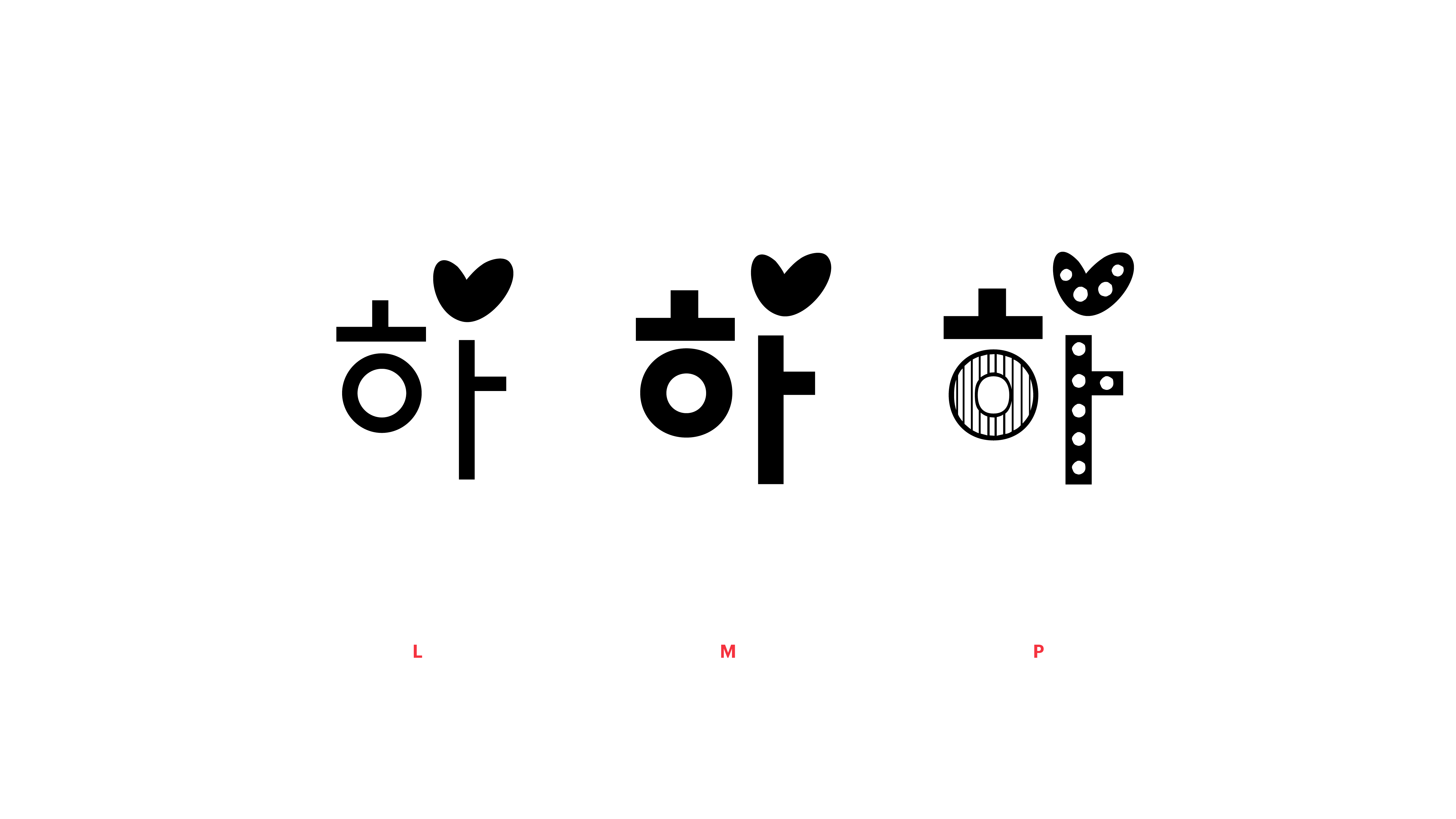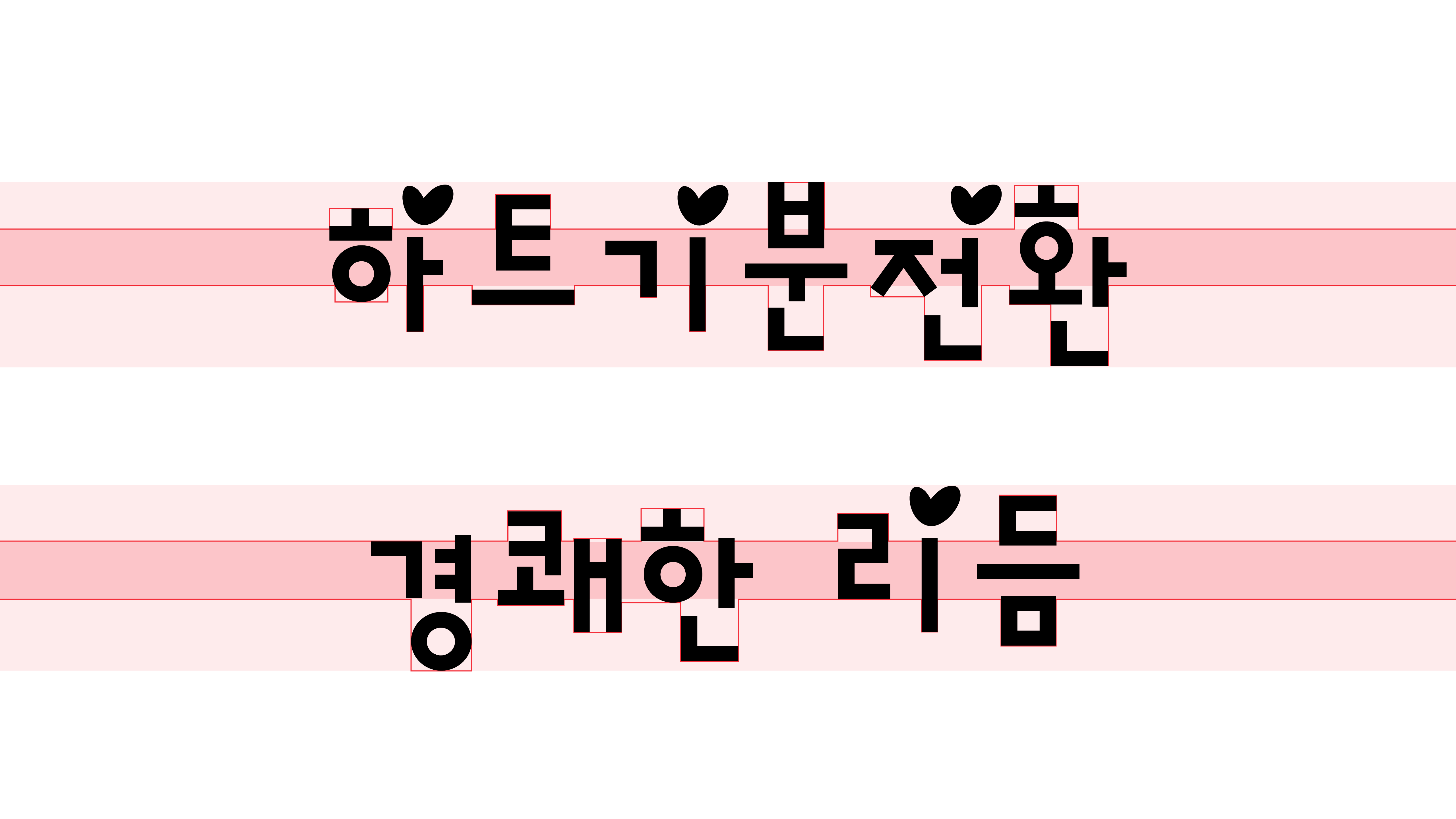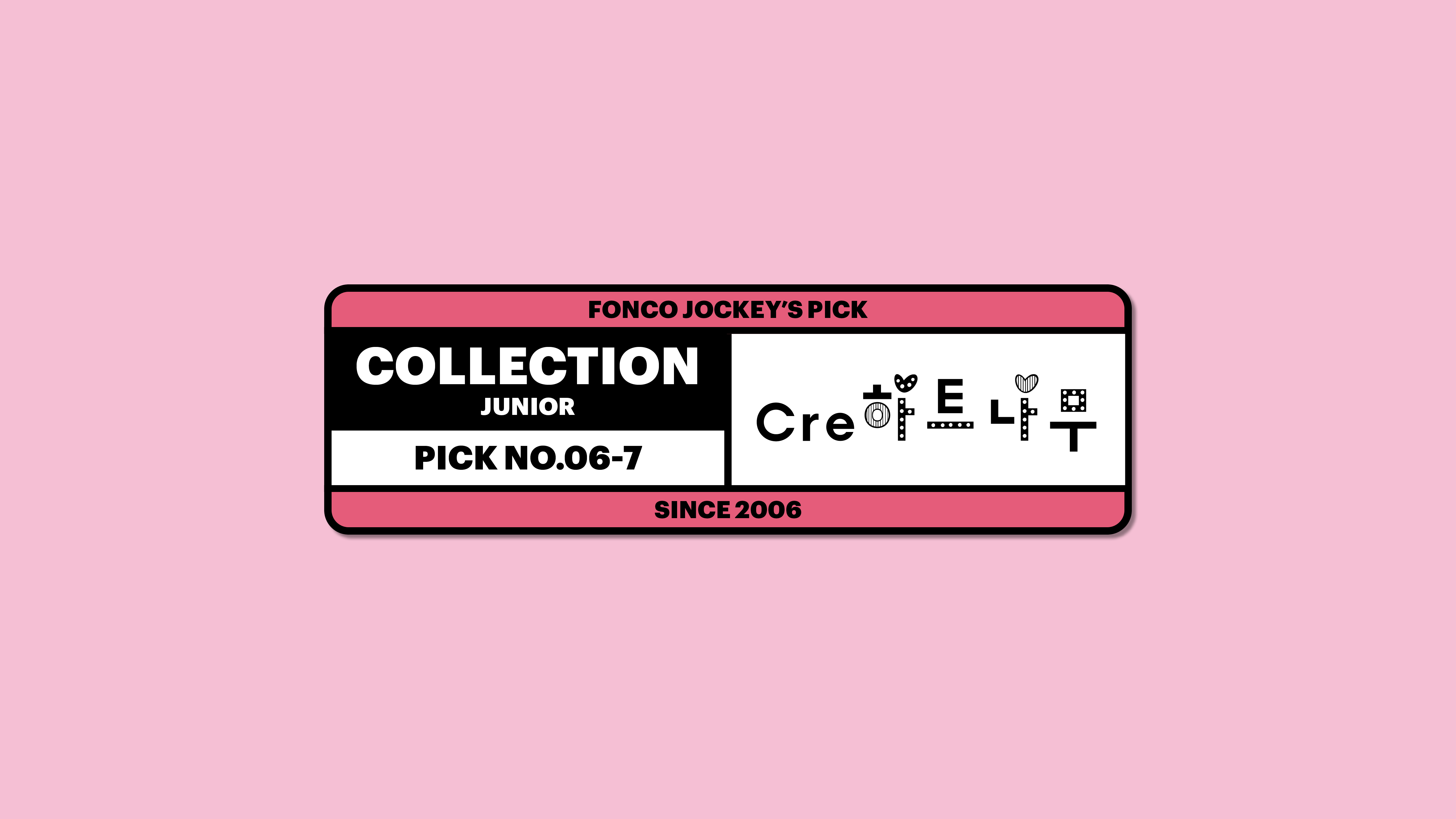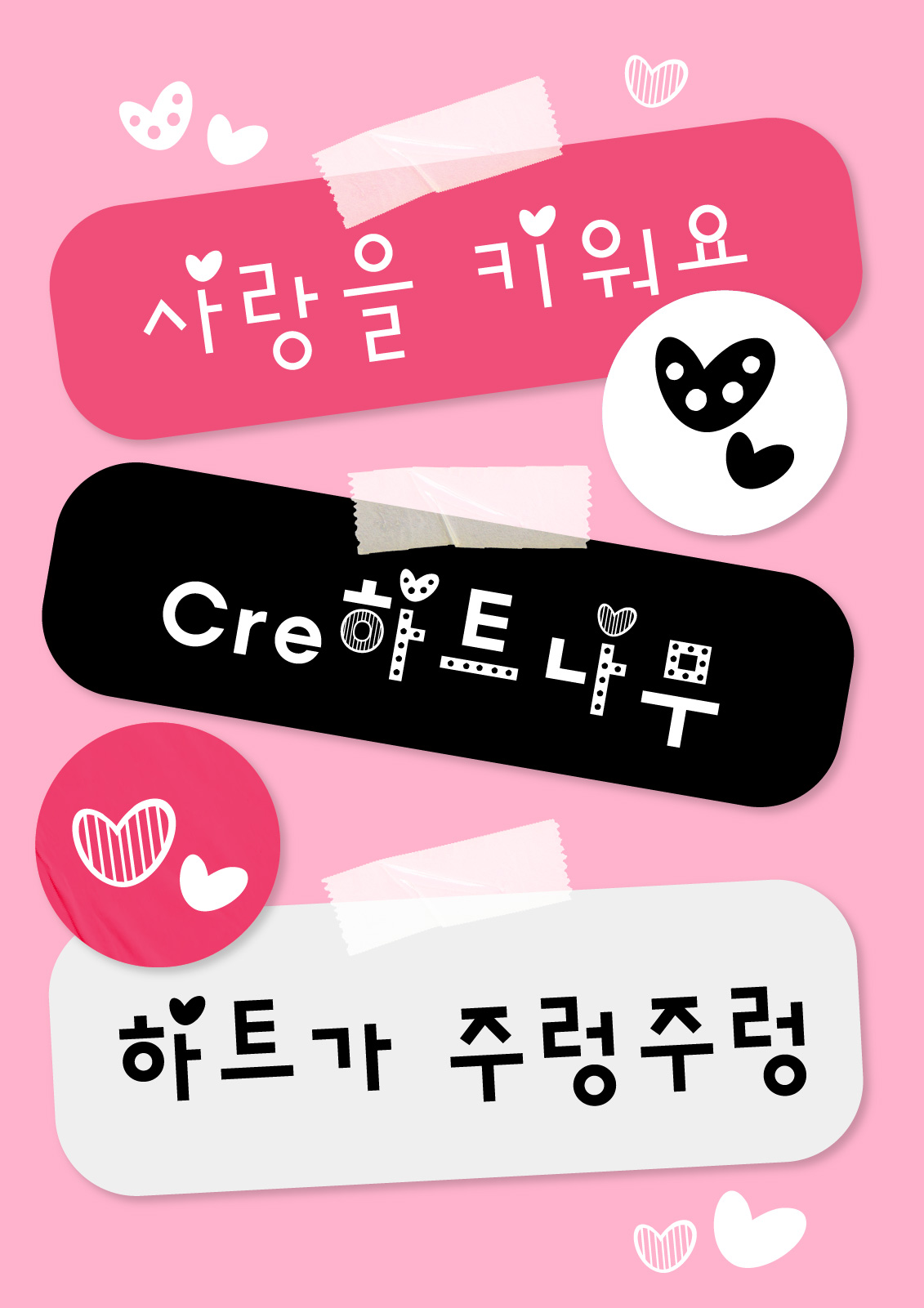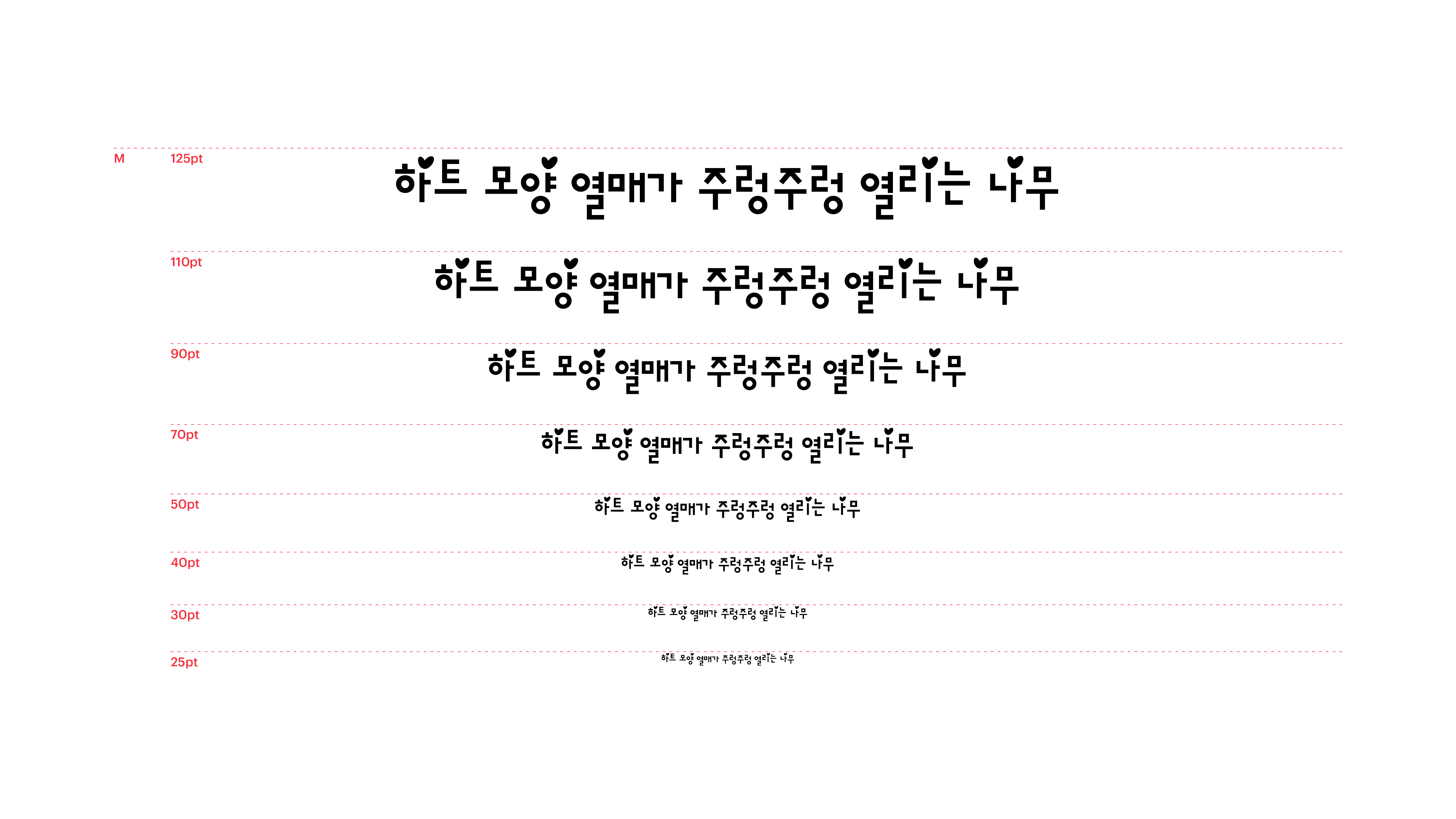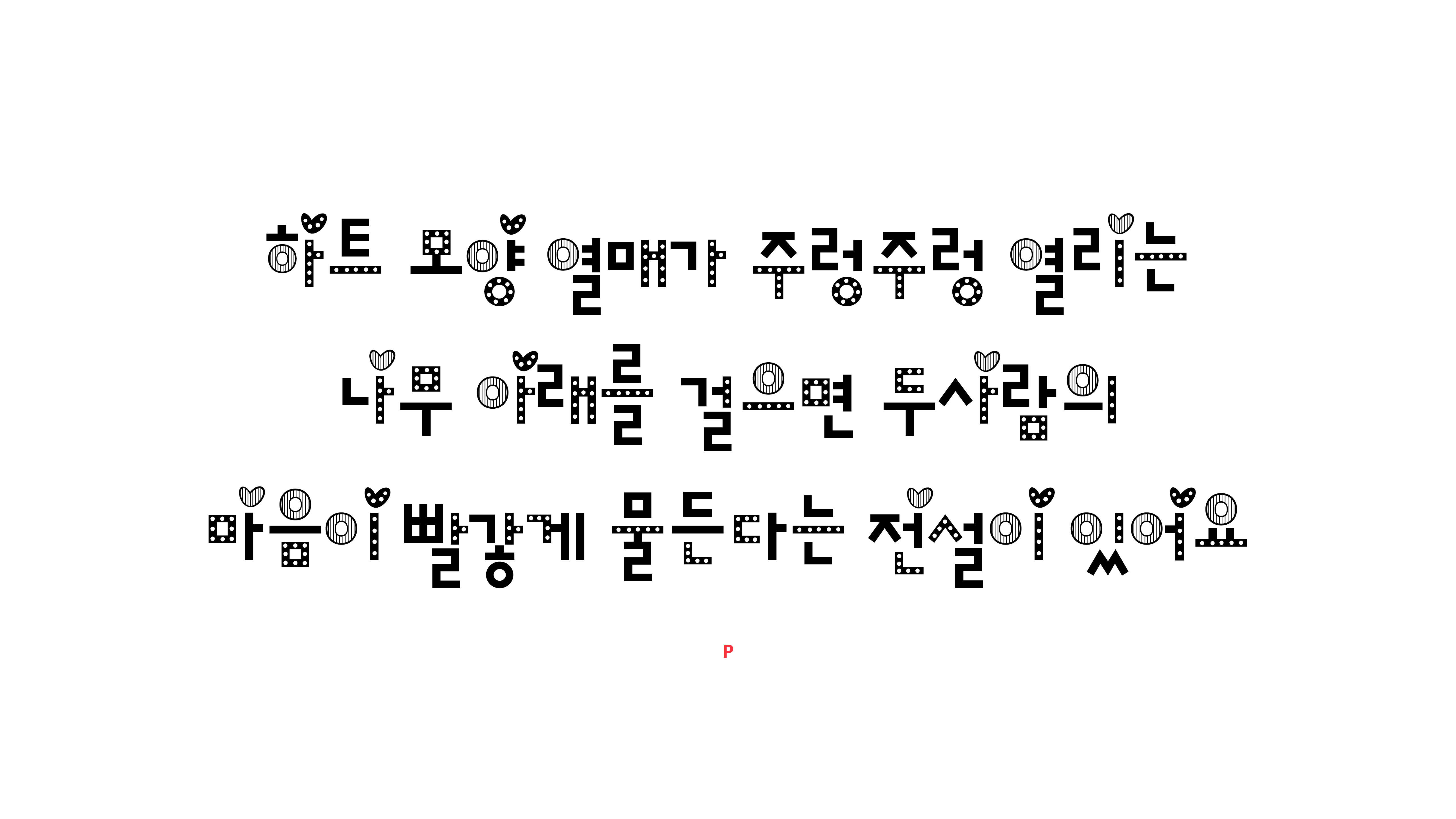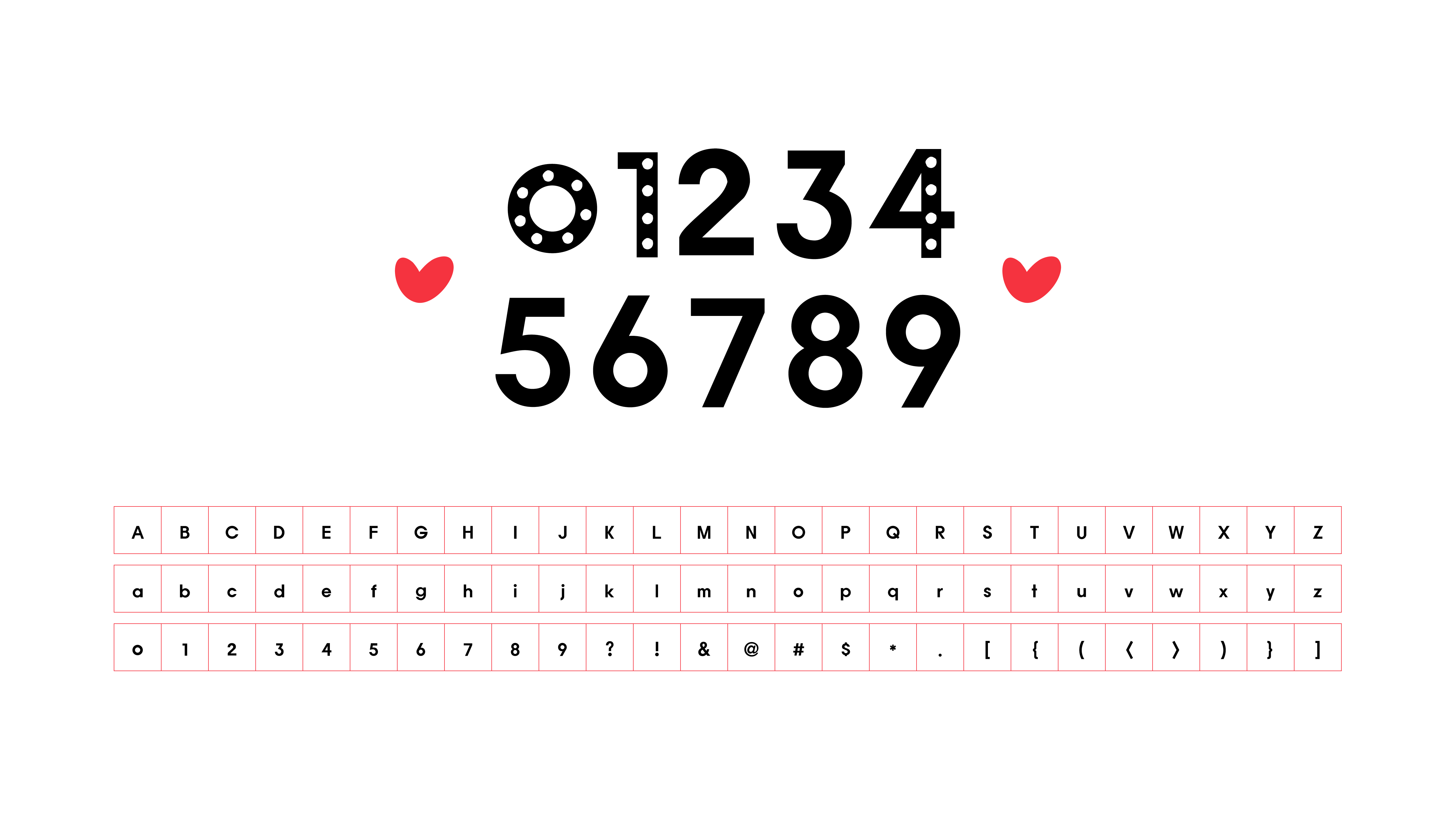
Cre 하트나무
Yoon Cre하트나무
유난히 되는 일이 없는 날, 다 내가 귀여운 탓이라며 애써 위로하고 있나요? Cre하트나무체로 속상했던 일을 쭉 적어보세요. 가운데에 글줄을 맞춰, 위아래로 경쾌하게 생겨난 리듬과 톡, 톡 튀어나오는 하트 모양 장식이 오늘의 구겨진 기분을 귀여움으로 가득 채워줄 거예요.